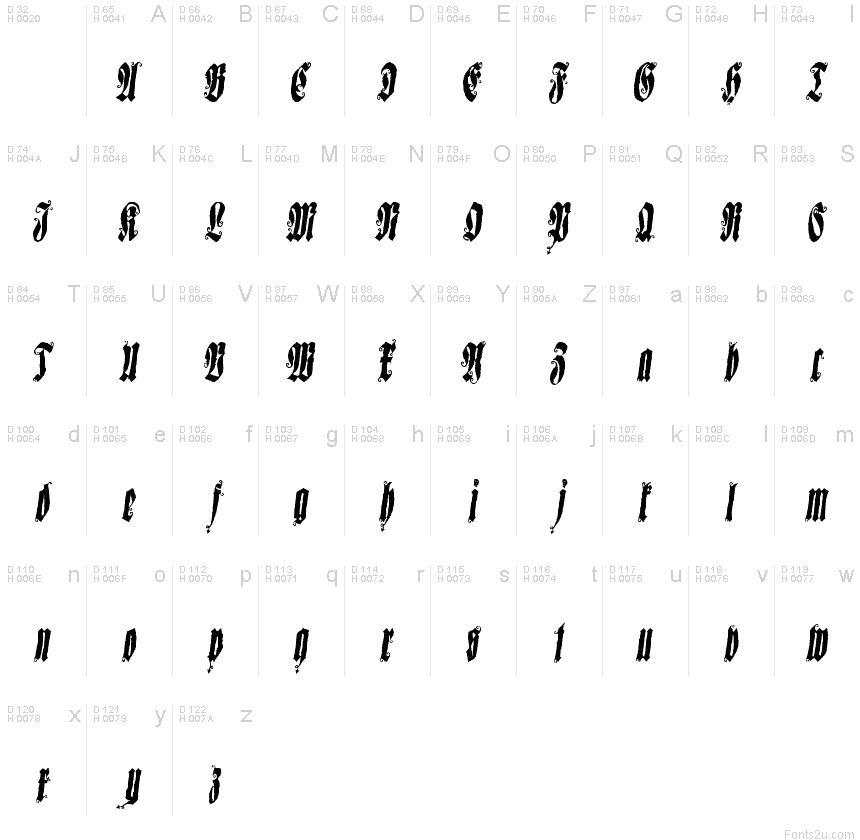
Sepultura autorstwa Dave'a Nalle to darmowy, średniowieczny krój pisma typu blackletter, który oddaje mroczny, surowy klimat dawnego gotyckiego liternictwa. Litery opierają się na wysokich, łamanych pociągnięciach i ostrych, klinowatych kształtach, ale to, co naprawdę je wyróżnia, to wijące się zakończenia, które dodają alfabetowi lekko kolczastego, dynamicznego charakteru.
Dzięki temu jest to naturalny wybór na okładki albumów, obwoluty książek fantasy, szyldy karczm, plakaty oraz do brandingu gier, gdzie zwykły darmowy font wydawałby się zbyt sterylny. Świetnie sprawdza się również w krótkich wstępach do rozdziałów, kartach tytułowych i monogramach, ponieważ haczykowate zdobienia oraz wąski, pionowy rytm nadają nawet kilku literom wyrazisty, historyczny klimat.